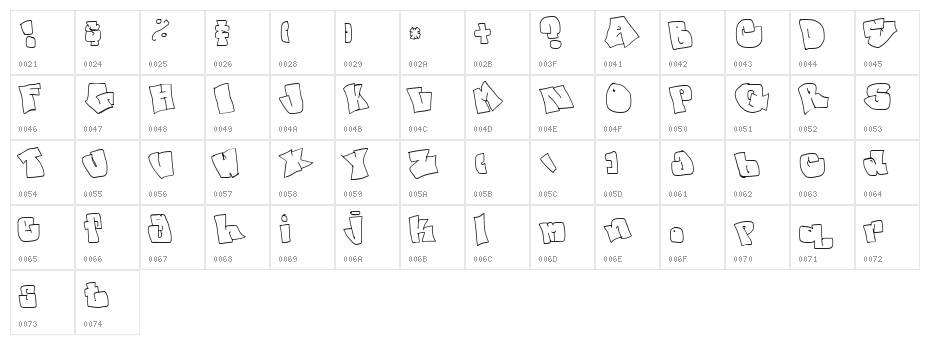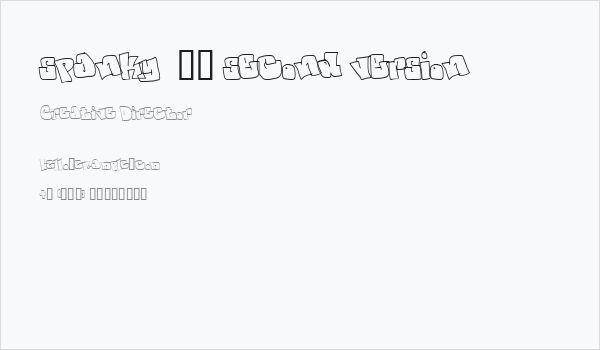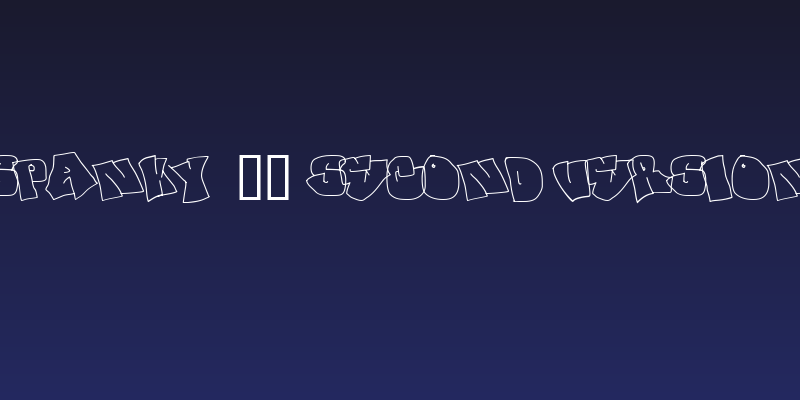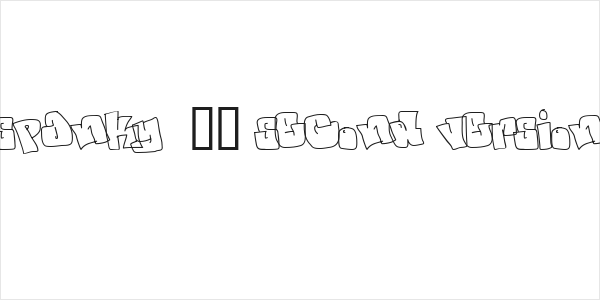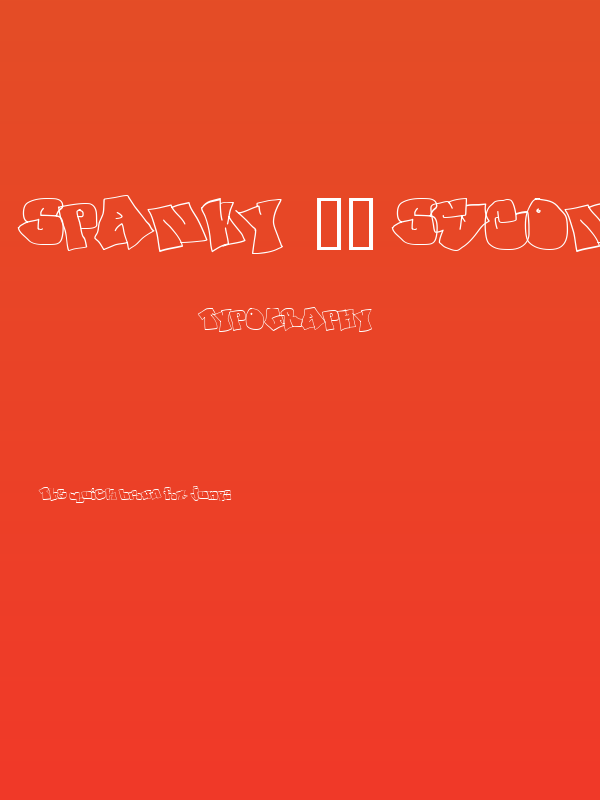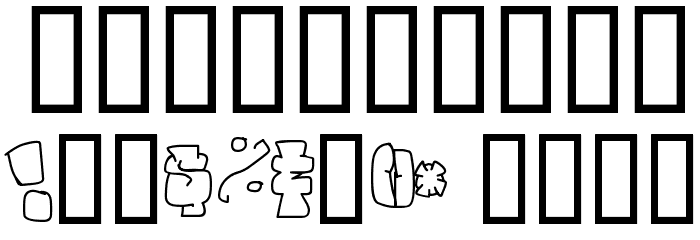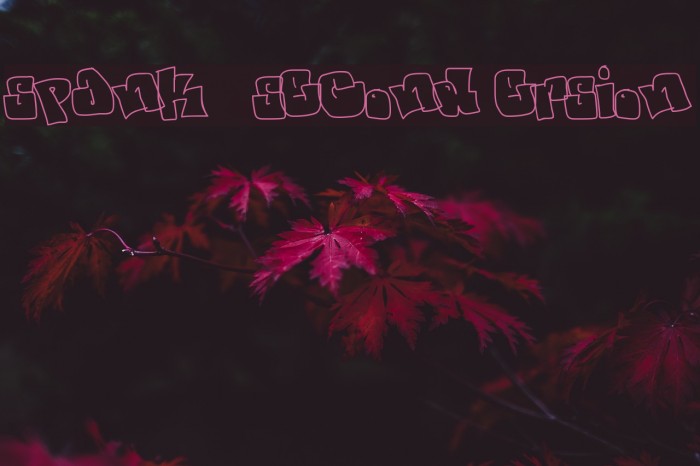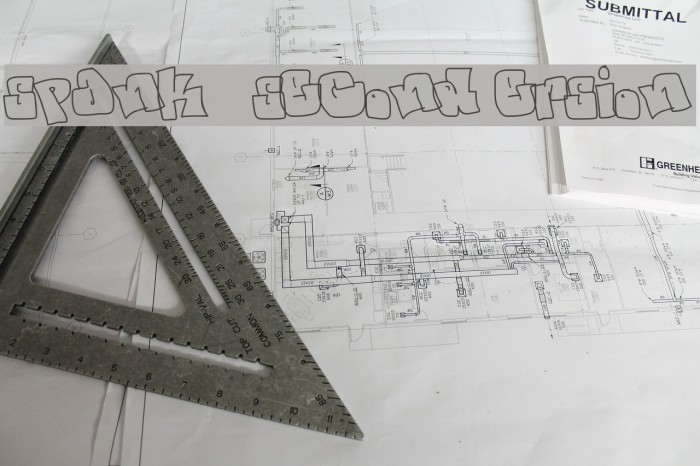
spanky 20 second version Font
✎ Graffiti
| Style général | Playful, Energetic, Graffiti |
| Projets proposés | Ideal for posters, children's books, event flyers, and creative branding. |